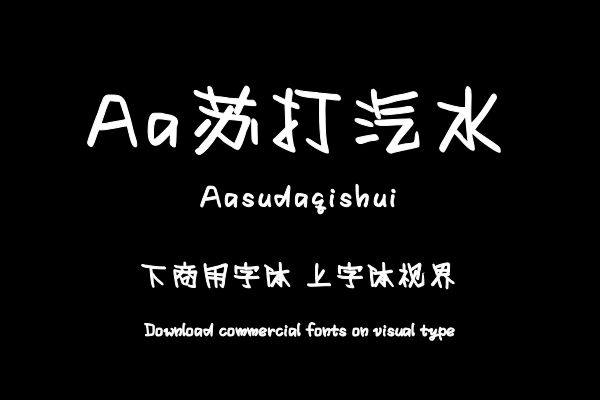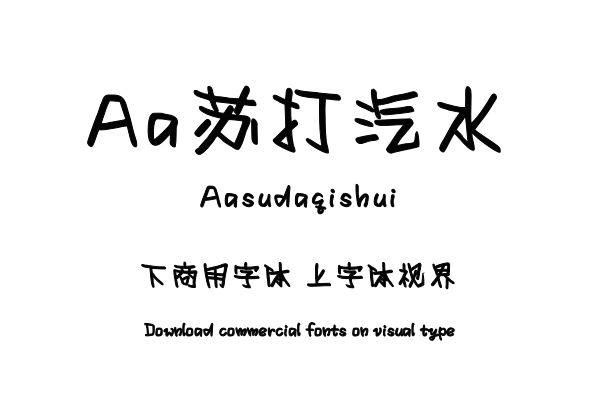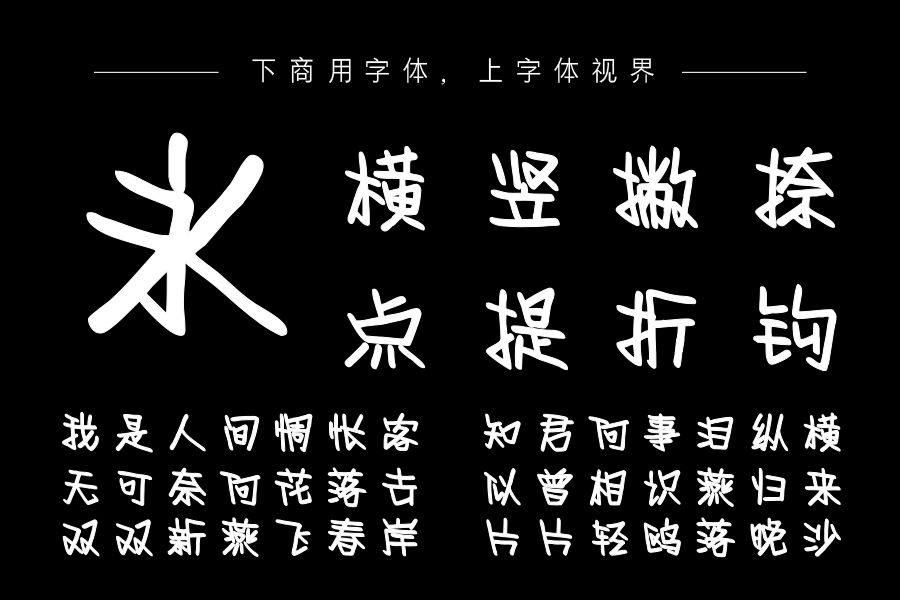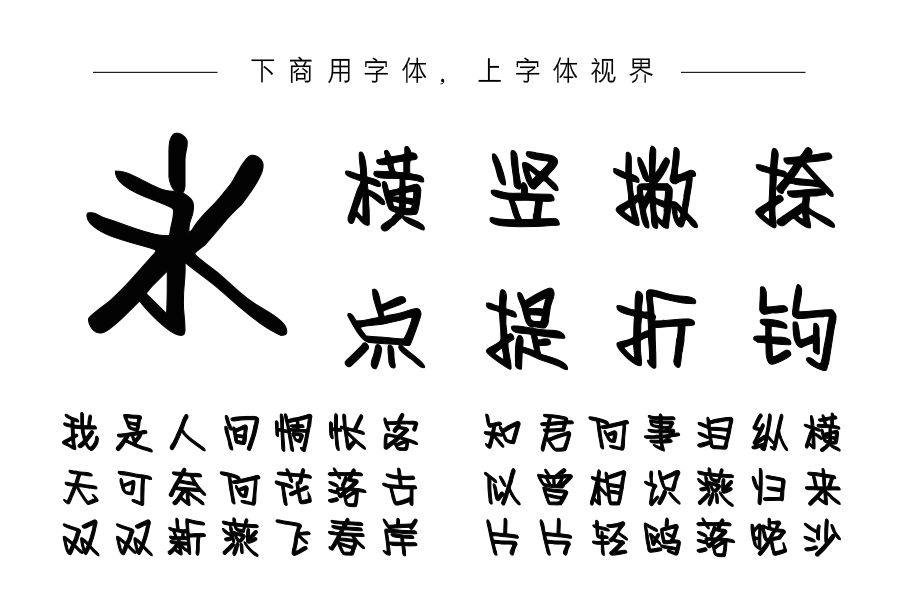
Aa苏打汽水,是一款POP结构风格的字体。字形方正,笔画粗细中等,书写潇洒有力,又不失规范。整体效果活泼有个性,多作为标题使用,适用场景广泛。购买须知:“下载服务费”与“字体VIP”所获得字体 仅用于个人非商用, 商用请联系付费授权。本字体为电脑用字,手机没有root权限不支持直接手机换字(手机如何root,请自行百度搜索教程)。购买前请先 了解清楚后再付款 ,字体为虚拟产品无法回收 一旦购买不支持退款。